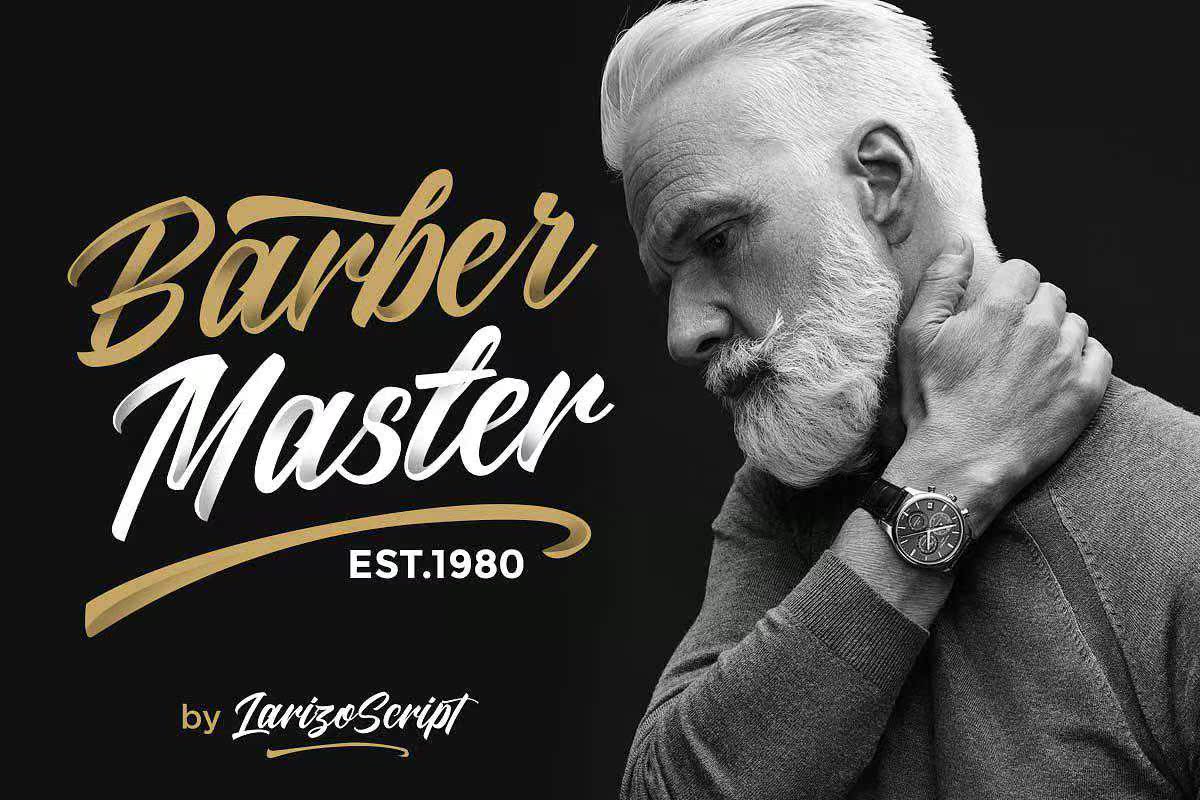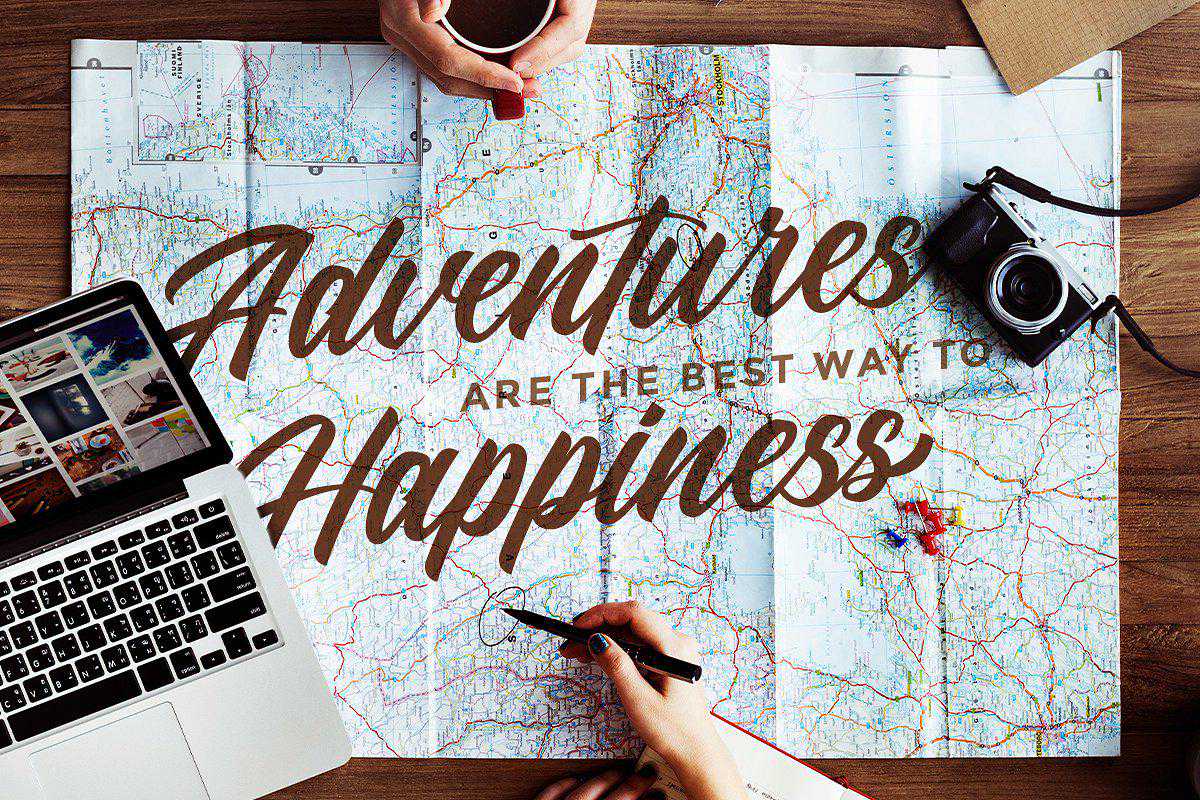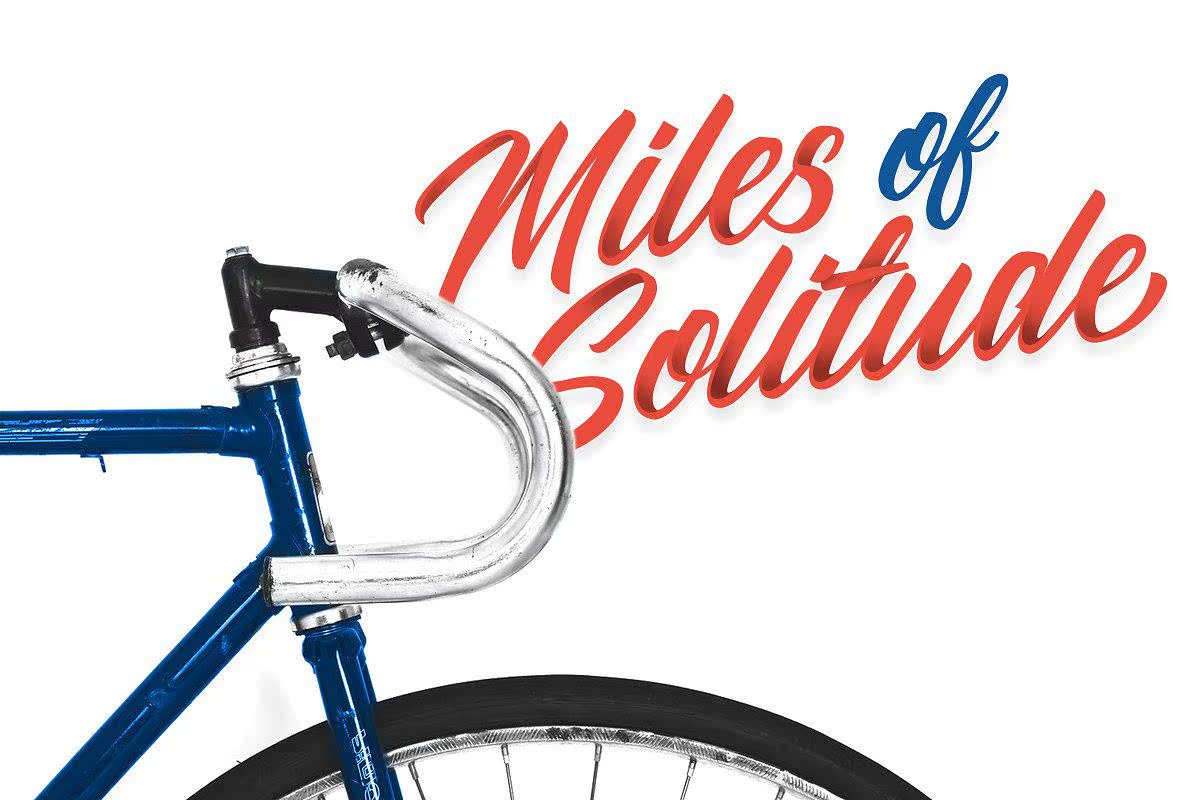
Larizo脚本。一个超文本个性化,并将其转换为字体!此字体具有独特的特征和流程,可以完美地使用非谷歌字体/文字标记、徽章、招牌、海报、头条文字、服装、婚礼宣传等。此字体具有多种五种类型的功能,包括广告、风格替换、上下文替换、swash等,并支持多种语言。您还可以同时使用谷歌和我的主题!Larizo脚本。一个超文本个性化,并将其转换为字体!此字体具有独特的特征和流程,可以完美地使用非谷歌字体/文字标记、徽章、招牌、海报、头条文字、服装、婚礼宣传等。此字体具有多种五种类型的功能,包括广告、风格替换、上下文替换、swash等,并支持多种语言。您还可以同时使用谷歌和我的主题!